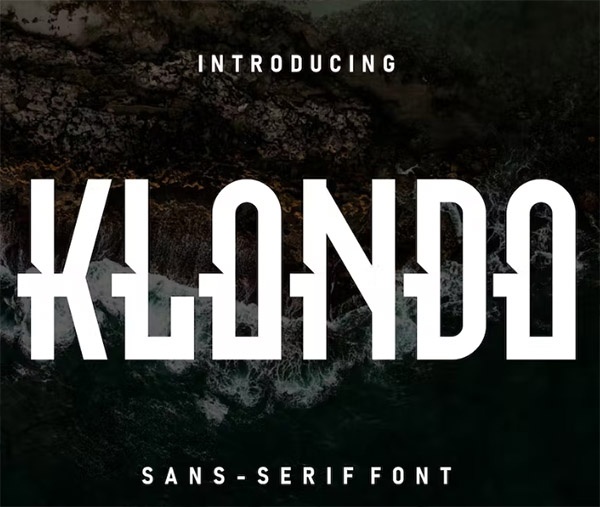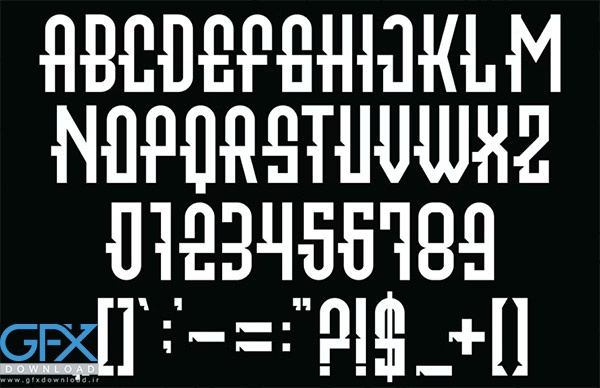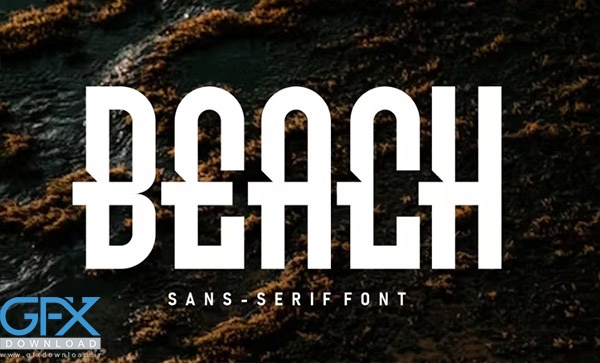
فونت انگلیسی Klondo
فونت انگلیسی مدرن Klondo
در این پست با معرفی یک فونت انگلیسی مدرن و جدید با نام فونت Klondo با شما همراه هستیم. فونت مدرن Serif که ظاهری زیبا، شیک و مدرن دارد. این فونت انگلیسی Klondo برای پروژه‌های مختلف مانند امضا، لوازم التحریر، لوگو، عروسی، نقل قول‌های تایپوگرافی، جلد مجله یا کتاب، سربرگ وب‌سایت، لباس، برندسازی، طراحی بسته‌بندی و غیره کاملاً مناسب است. همچنین، برندسازی مرتبط با مد یا طراحی سرمقاله، ویژگی‌های مردانه و زنانه را نشان می‌دهد.